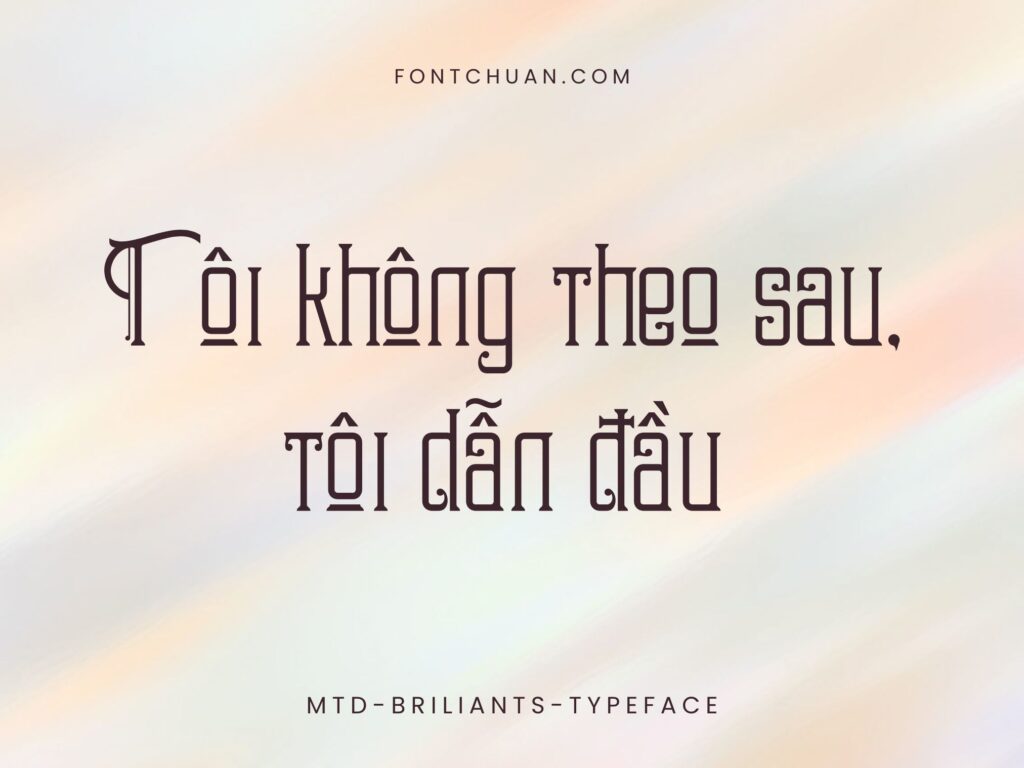
Font MTD Briliants Typeface Việt Hóa
Briliants Typeface là một font chữ thanh lịch với thiết kế tinh tế, mang phong cách hiện đại pha lẫn nét cổ điển. Font này có kiểu dáng sang trọng, giúp tăng tính chuyên nghiệp và tạo điểm nhấn đặc biệt cho các dự án thiết kế. Để hỗ trợ cộng đồng thiết kế Việt Nam, Mộc Hạ đã Việt hóa font Briliants Typeface, giúp font này hỗ trợ đầy đủ tiếng Việt cùng hơn 200 ngôn ngữ khác. Phiên bản Briliants Typeface Việt hóa đã được thành viên Font Chuẩn sưu tầm và đăng tải, nhằm mang đến sự lựa chọn phong phú hơn cho các nhà thiết kế.
Về đặc điểm thiết kế, Briliants Typeface sở hữu những đường nét sắc sảo, tạo nên sự sang trọng và ấn tượng trong các thiết kế thương hiệu, tiêu đề, typography sáng tạo và bao bì sản phẩm. Font này rất phù hợp với các lĩnh vực như quảng cáo, bất động sản, giáo dục và công nghệ, mang lại phong cách hiện đại và chuyên nghiệp. Ngoài ra, Briliants Typeface cũng là một lựa chọn lý tưởng cho các sự kiện như Valentine, Sinh nhật và các lễ hội.